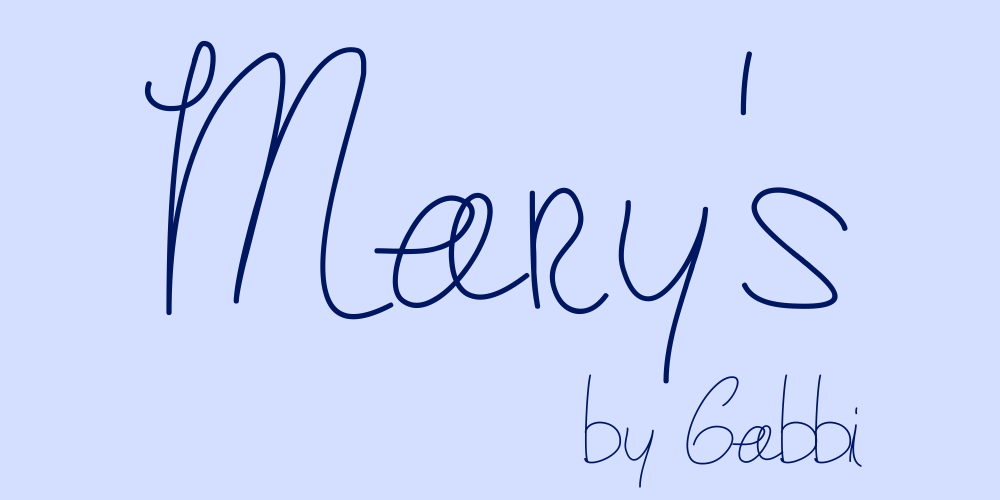
A Mary’s Handwriting é uma fonte de escrever a mão que transmite suavidade e simplicidade ao mesmo tempo. Seu designer, Hamilton, captura a essência da escrita humana, resultando numa fonte fluida e envolvente. Com traços leves e harmoniosos, essa fonte é perfeita para criações que buscam um toque delicado e pessoal. Ideal para designers de gráficos buscando dar uma nota única a suas criações digitais, Mary’s Handwriting oferece um grau único de personalização. Seja você criando um site web com um estilo mais cuidadoso, trabalhando em desenhos animados que precisam de uma cara mais intimista e humana, ou produzindo material para redes sociais que precisa parecer fresco e emocionalmente conectado, essa fonte é perfeita. Não apenas proporciona uma variedade única de opções para o seu design, mas também oferece um toque delicado capaz de criar uma conexão pessoal entre você e sua audiência. Mary’s Handwriting não só adicionará um toque agradável ao seu trabalho, mas também fornecerá aos seus clientes um produto visualmente atraente que chama a atenção. Essa fonte é perfeita para qualquer aplicação onde há um desejo de simplicidade e uma maneira amigável de conectar-se com o espectador.